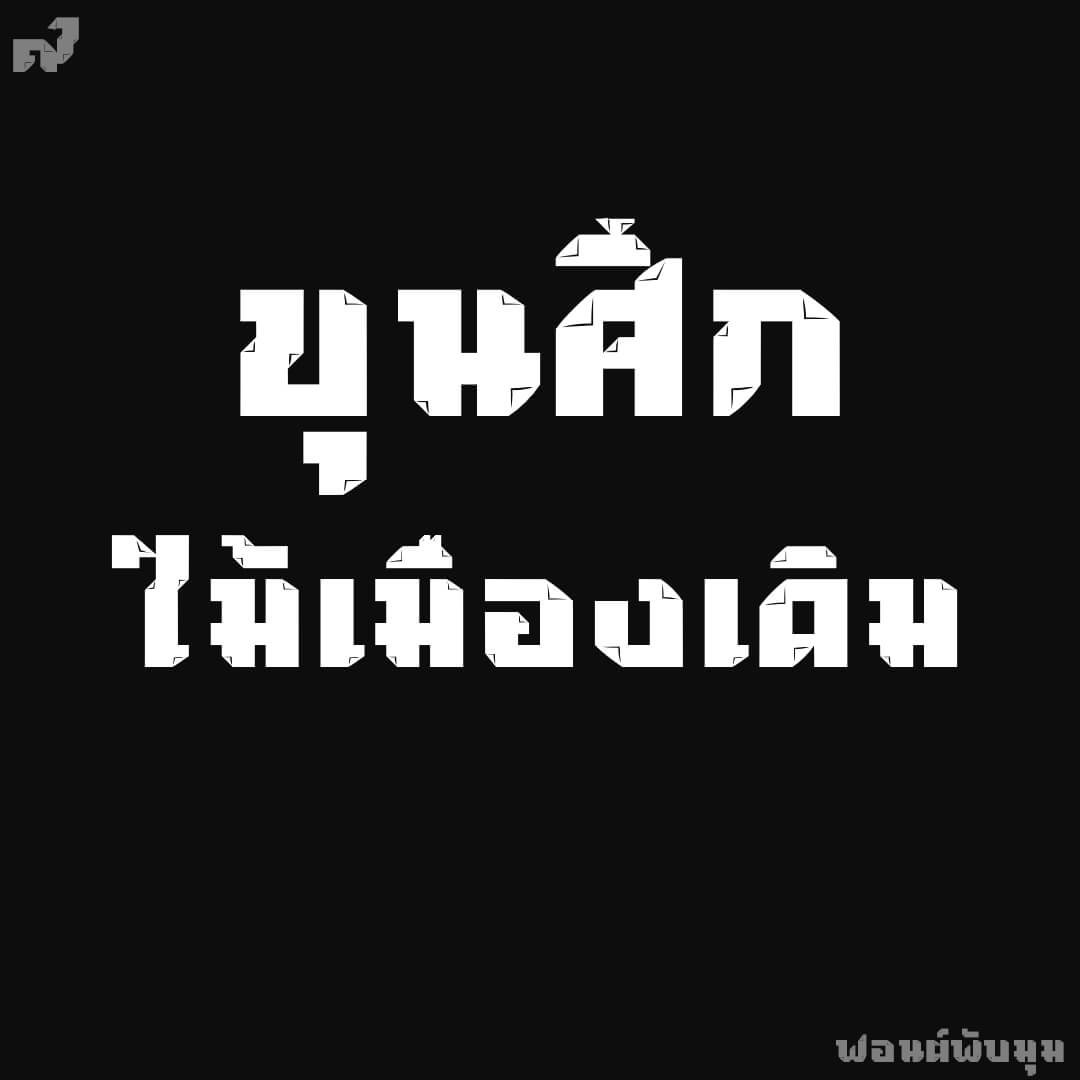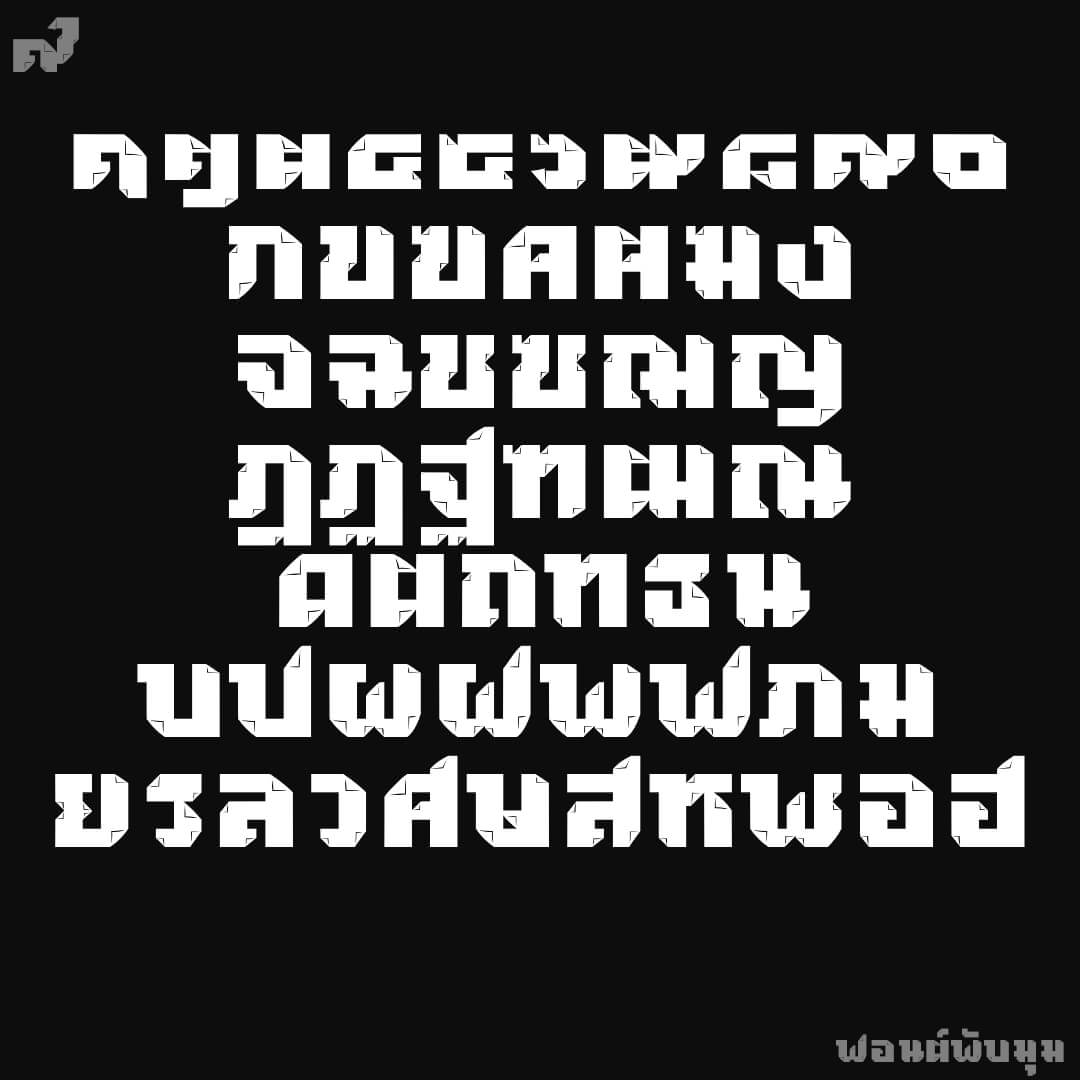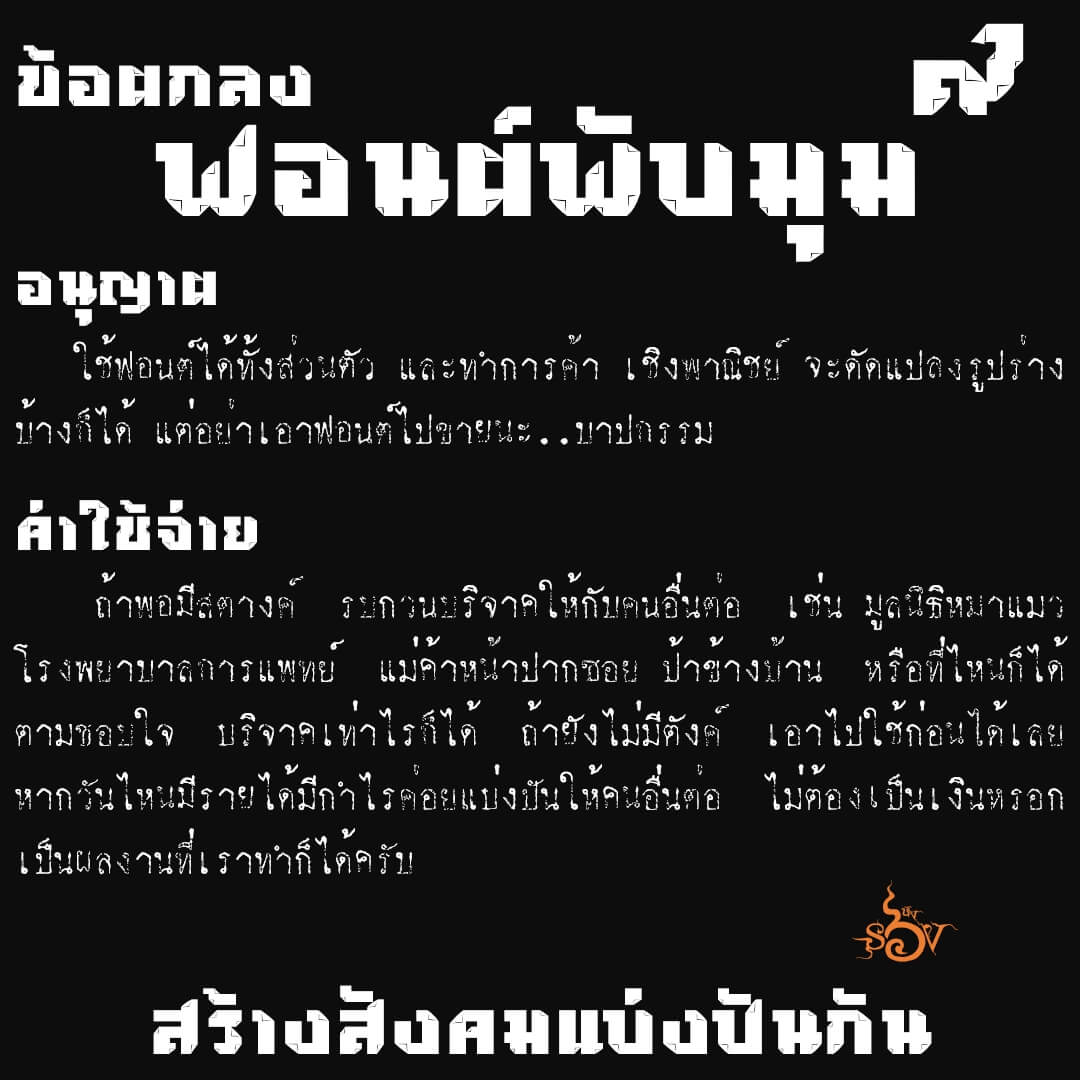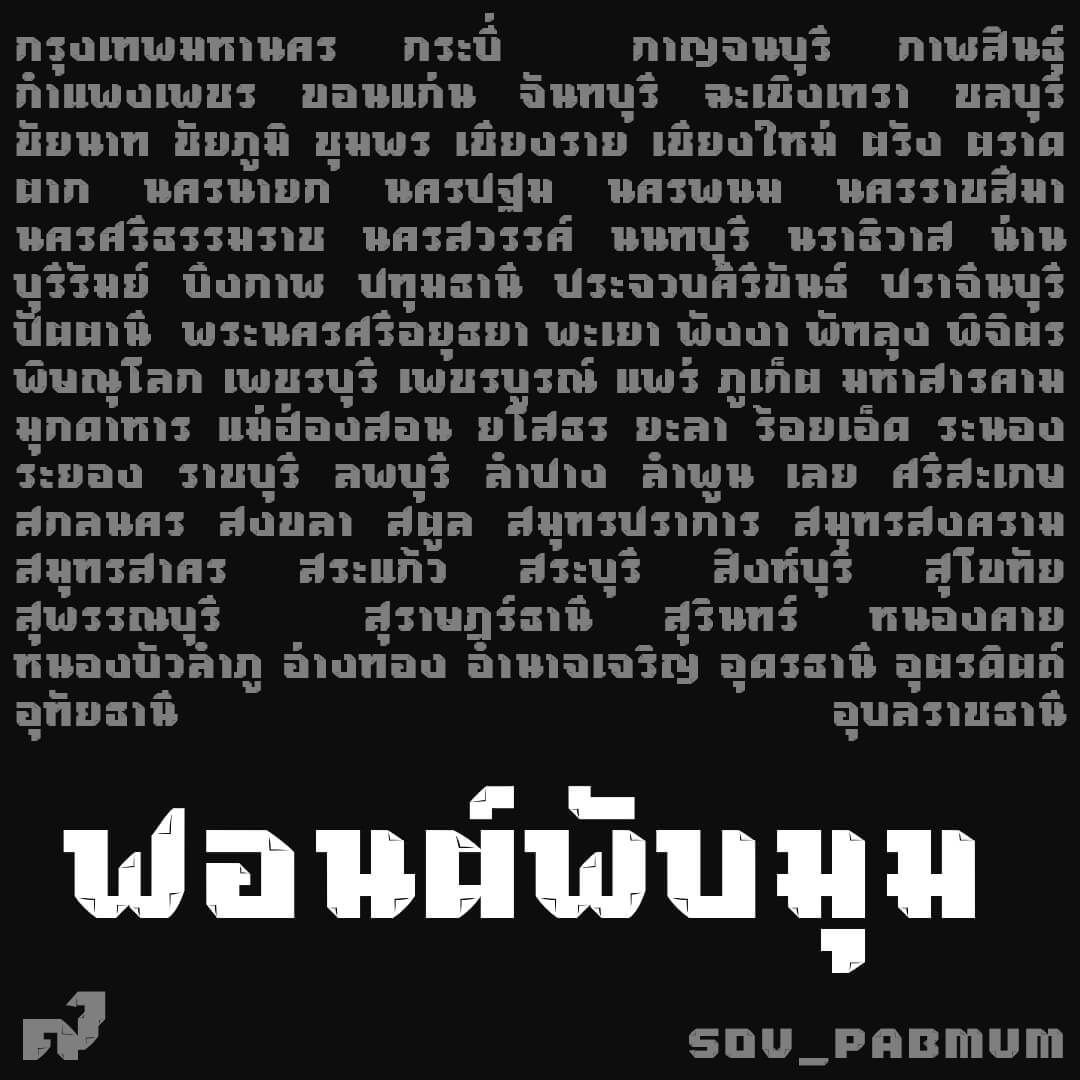
ฟอนต์พับมุม – แนวทางจากปกหนังสือ ขุนศึก ต้นทางเป็นรูปแรเงารอยพับกระดาษ นำมาปรับเป็นลายเส้นอย่างเดียว
เบื้องหลังการออกแบบ : ฟอนต์ พับมุม
พับมุม (SOV_Pabmum)